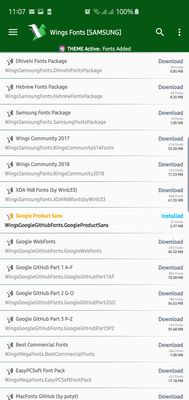
Hướng dẫn cài Google Fonts rất đẹp lên Samsung Galaxy chạy One UI, không cần root
Mình sd font này, font của bác chủ topic hơi cứng.
Font này chung font với các app của google ko mấy bạn?
Ai biết font chữ các app gg đang sử dụng tên là gì ko ạ?
@nb3105 bài viết là chỉ đổi qua font này đó bạn, GoogleProductsSans